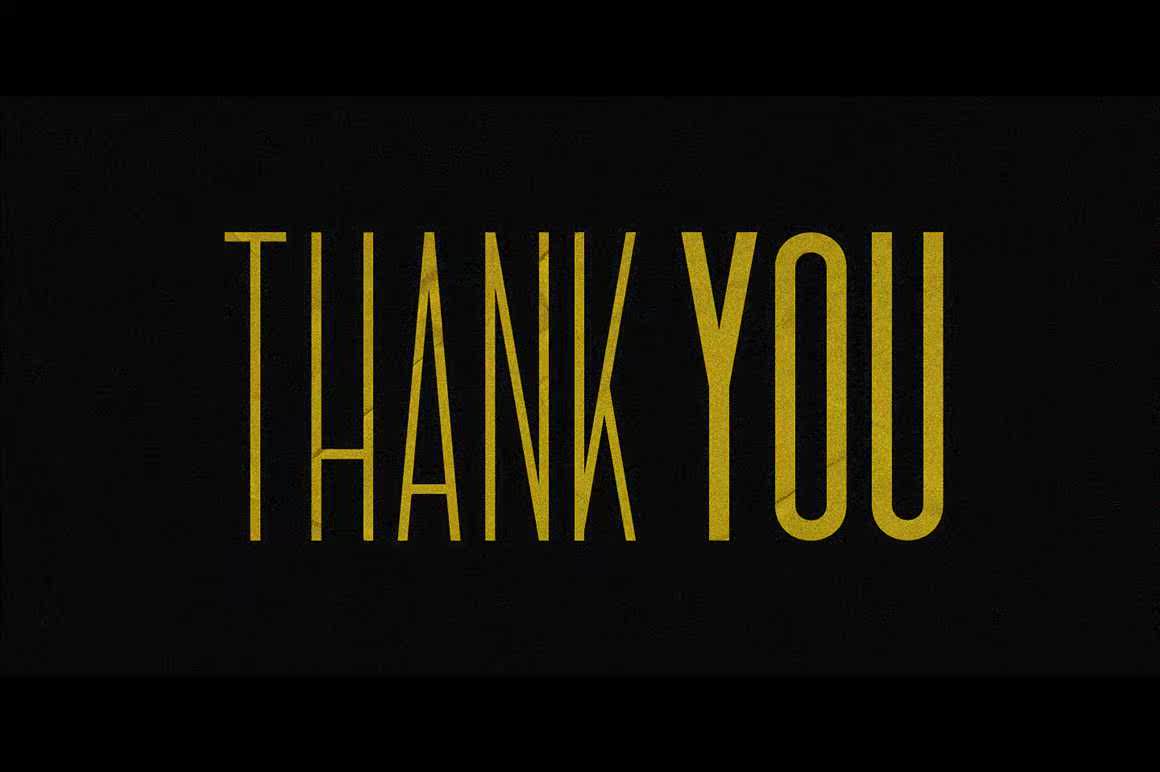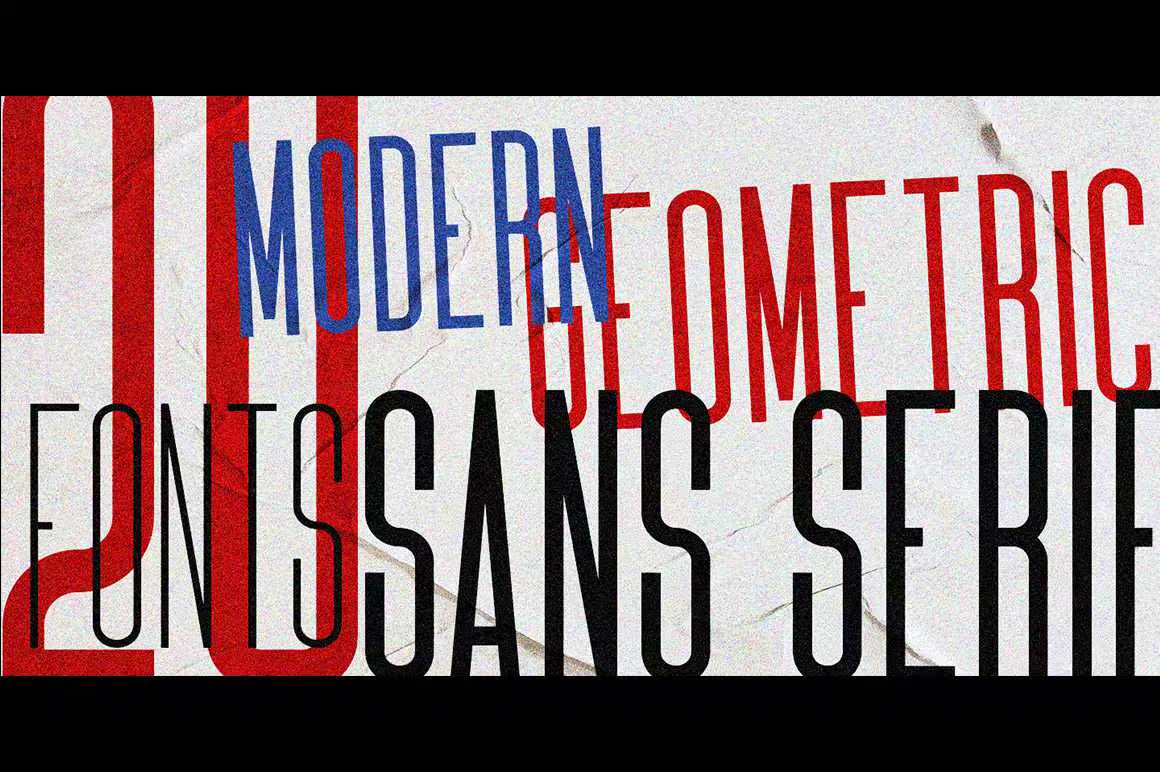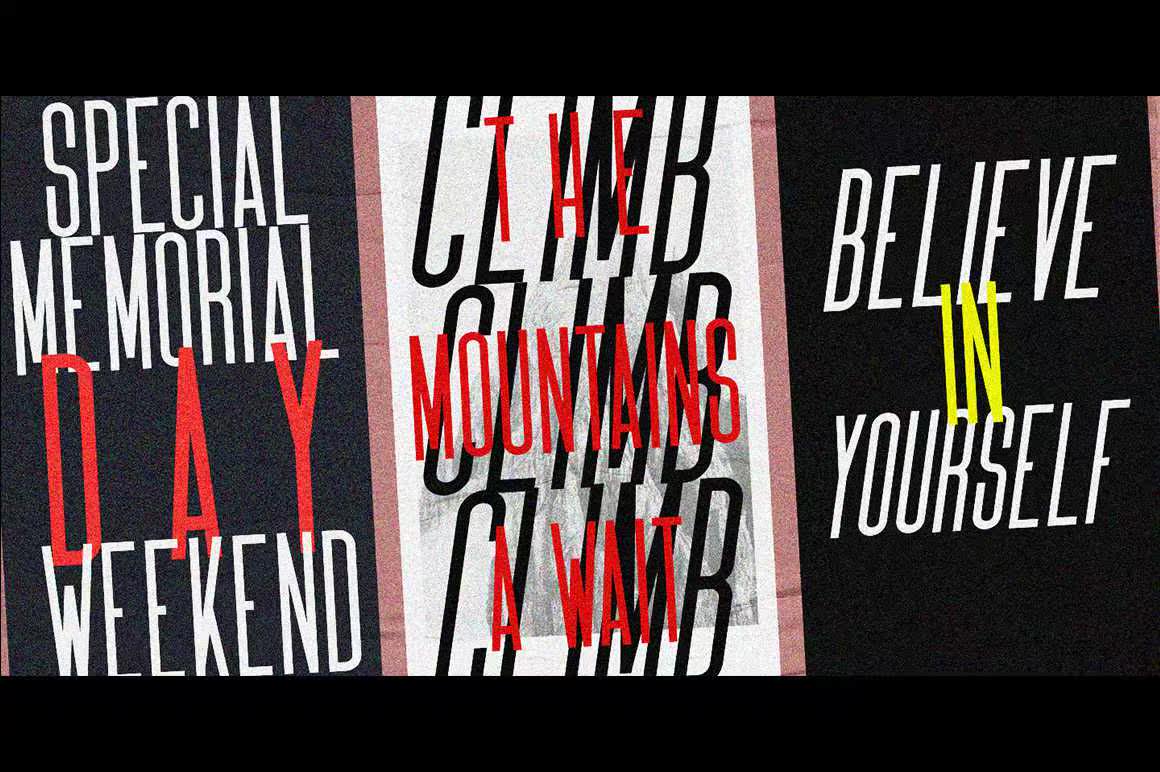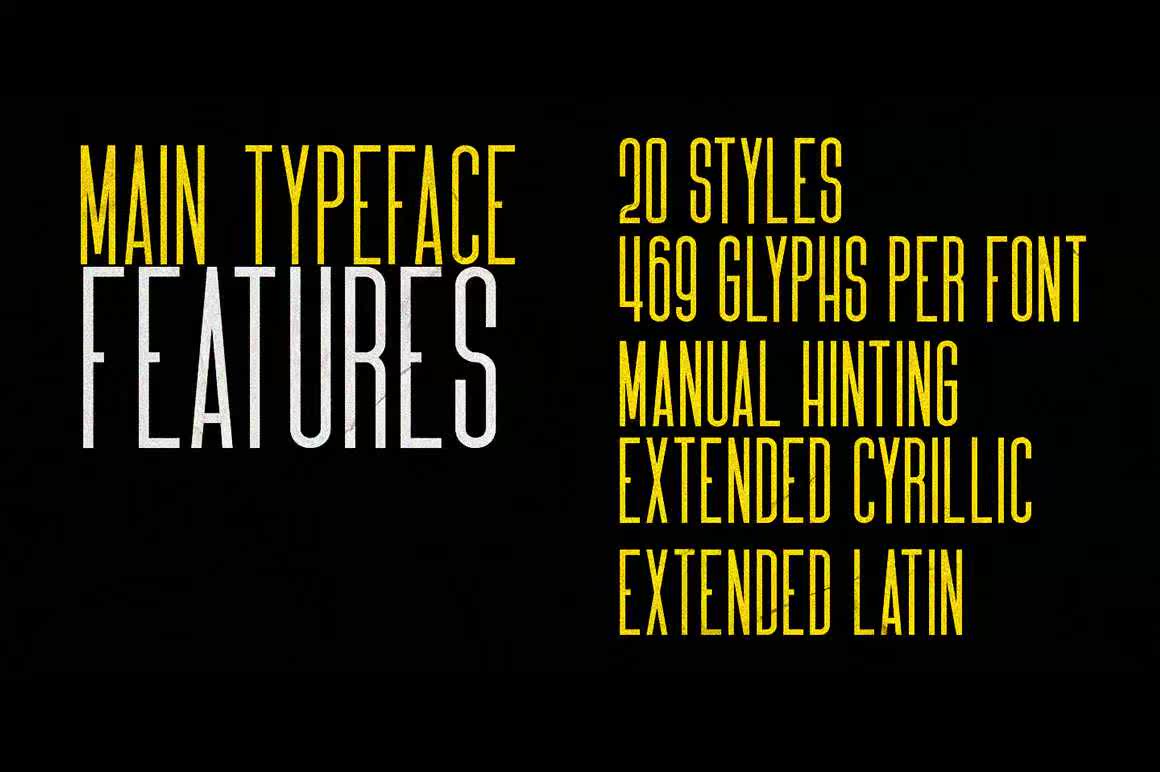
Freya是一个强大的Font家族,也是一个成熟的Sansserif。他坚定而不妥协的风格是通过文字来体现的,这些文字都是以一种非常强硬的平衡和平滑的曲线来控制的。家族中的每一个成员都是独立的、动态的和权威的。我提供广泛的语言支持,包括所有中西语言,越南和非洲语言。弗雷亚是一个强大的方家族和复杂的梵语。他坚定而不妥协的风格是通过文字表现出来的,这些文字都是由一种非常强硬的平衡和平滑的曲线控制的。家族中的每一种语言都是独立的、动态的和权威的。我提供广泛的语言支持,包括所有中部和西部的语言,越南和非洲的语言。